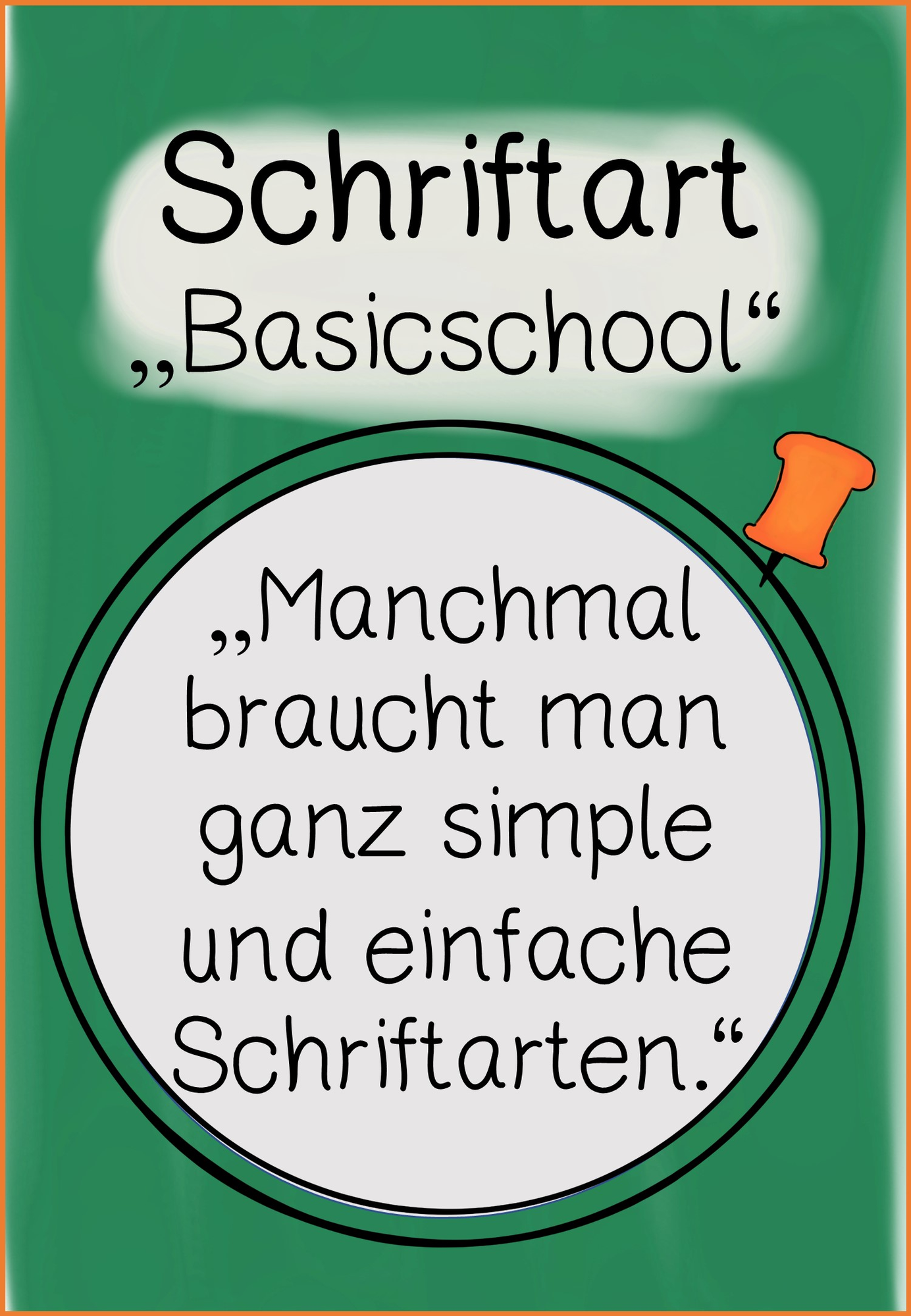
selbst erstellte Schriftarten - Schriftart "Basicschool" - grundschulliebe_s - Deckblatt
Eine Schriftart, die meiner persönlichen Handschrift sehr ähnlich ist und die sehr simpel gestaltet ist.
Schriftart "Basicschool"